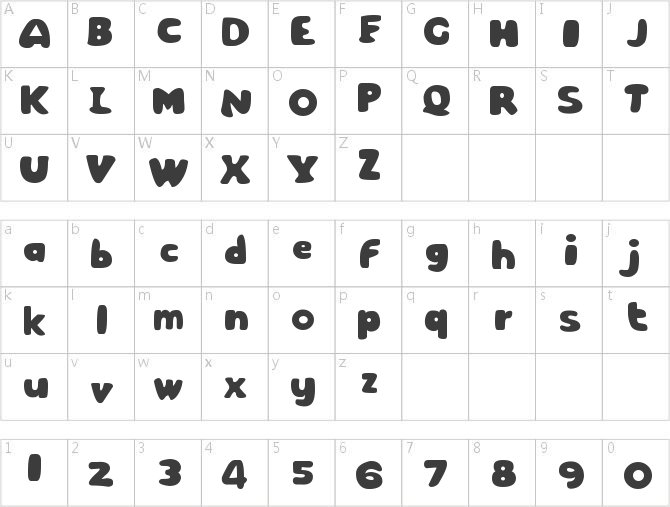
字體名稱: Easter
Easter ABC Egg Two
Easter ABC Egg Two介紹
Easter ABC Egg Two字體字庫是一款讓人賞心悅目、百看不厭的英文字體,適合各類廣告和產品包裝設計應用,字體大小0.02MB,格式為ttf字體,上傳用戶是曾紹文,作者/版權方為未知